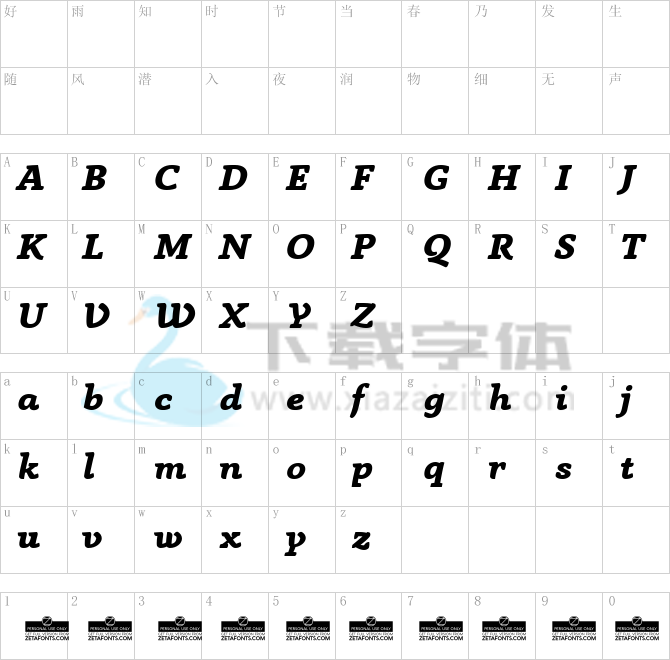
Anaphora Trial.ttf字体下载,这款字体结构工整、笔画清晰,兼顾美观与易读性,适用于标题、正文、海报、包装、LOGO 等多种场景。字形优雅稳定,风格百搭耐看,适配日常排版与创意设计,让文字呈现更舒适、更具质感。Anaphora Trial.ttf字体下载一笔一画,皆是细节,以均衡的比例、流畅的线条打造舒适视觉体验,字形端正大气,风格简约现代。无论是商业设计、品牌宣传还是日常排版,都能轻松驾驭,让文字更有格调与力量。Anaphora Trial.ttf字体下载字体下载。